Akzidenzsatz
»Akzidenzsatz« bezeichnet einen gewerbespezifischen Fachbegriff aus der Zeit der Offizinen des 16. Jahrhunderts, der sich ab dem späten 18. Jahrhundert in Zeitungs- und größeren Buchdruckereien mit spezialisierten Akzidensatzabteilungen durchsetzte. Das Pendant zum Akzidenzsatz ist der Werksatz.
Der Akzidenzsatz unterschied sich vom klassischen Werksatz dadurch, dass er vor allem für die Gestaltung von Akzidenzdrucksachen verwendet wurde – also für Zeitungsköpfe, Werbeanzeigen, Plakate sowie Geschäfts- und Privatdrucksachen.
Semantisch rührt der erste Teil des Kompositums von »Akzidenzen«, etymologisch von mittellateinisch »accidentia« über mittelhochdeutsch »accidenz« zu »Akzidenz« im Sinne von »etwas Zufälliges, Nebensächliches, Nebenarbeit«. In der Typografie und im Druckwesen bezeichnete »Akzidenz« seit dem 16. Jahrhundert »Gelegenheitsarbeiten« oder »Nebendrucksachen« im Unterschied zu den Hauptwerken einer Offizin wie Bibeln, Gesangbüchern oder wissenschaftlichen Werken, z.B. Flugblätter, die sowohl religiöse als auch politische Themen behandelten. 1) Der zweite Teil des Kompositums verweist auf den Schriftsatz, also das satztechnische Verfahren.
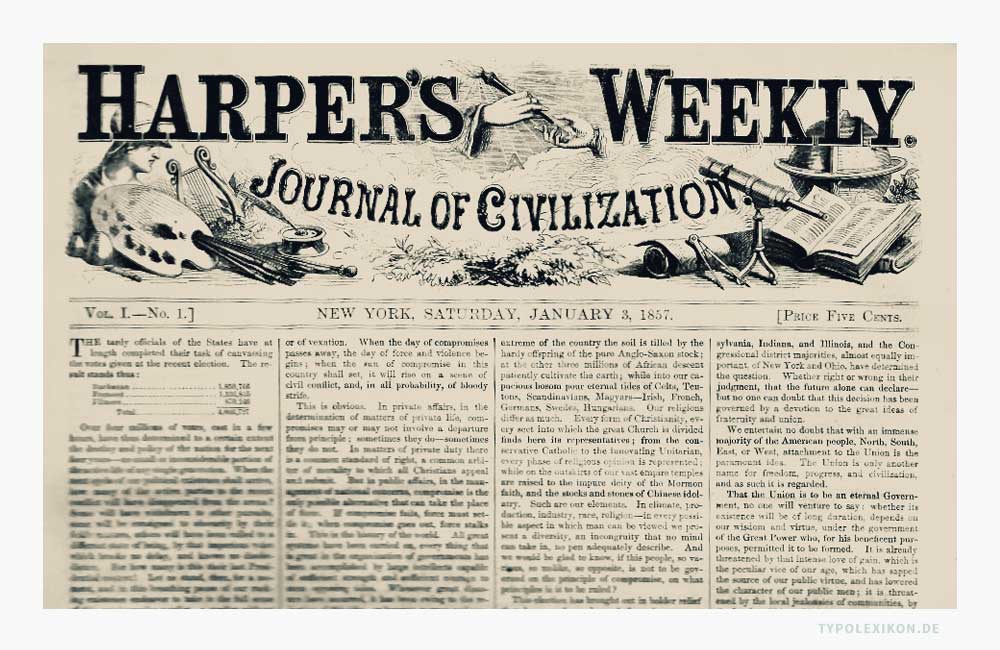
Im Akzidenzsatz arbeiteten besonders geschulte Akzidenzschriftsetzer mit sogenannten Akzidenzschriften, die in der Regel aus Metall (z.B. aus einer Blei-Zinn-Antimon-Kupfer-Legierung oder Messing), Holz (z.B. aus Birnenholz) oder Kunststoff (z.B. aus Kunstharz) bestanden. Aus der Akzidenzschriftsetzerei entwickelte sich sukzessive ab den 1960er Jahren mit der Einführung des Fotosatzes (optomechanischer Schriftsatz) die Layout-Setzerei, die meist als eigenständiges Unternehmen außerhalb einer Druckerei fungierte. 2) 3) 4)
| ↑1 | Anmerkung: Zu den bekanntesten Flugblättern zählen u.a. Reformationsflugblätter von Martin Luther und anderen Reformatoren, Flugblätter zum Deutschen Bauernkrieg (1524–1525), die die Anliegen der Bauernbewegung unterstützten oder die Obrigkeit kritisierten. Diese Flugblätter spielten eine wichtige Rolle in der Mobilisierung und Kommunikation der Bauern, sowie satirische Flugblätter, die sich über politische und religiöse Themen lustig machten. Ein Beispiel hierfür ist ein französisches Spottblatt auf den Papst aus dem Jahr 1551. |